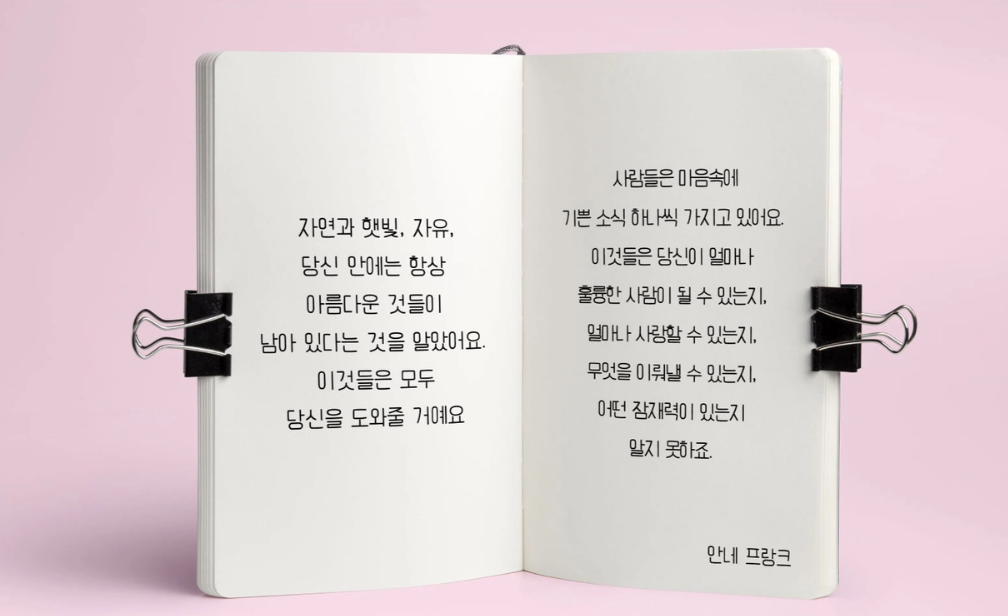
다이어리체 — 얼리폰트에서 배포하는 무료 폰트입니다. 또박또박한 필기감에 자연스러운 글자 변화를 더한 아담하고 정감 있는 손글씨체
얼리폰트가 배포하는 손글씨 서체입니다. 얼리폰트는 기업 전용서체 제작을 본업으로 하는 회사인데, 이 서체를 무료로 풀어 이름을 알린 것으로 알려져 있습니다.
제작사가 쓴 소개가 성격과 쓰임을 한꺼번에 말해 줍니다. 한 글자 한 글자 반듯하게 다이어리에 쓴 글씨처럼 손글씨지만 반듯한 매력의 서체이고, 유튜브 자막이나 귀여운 폰트가 필요한 곳에 추천한다는 것입니다. 파일에서 재어 보면 받침 유무에 따른 높이 차가 거의 없는 네모틀이라, 손글씨인데도 글줄이 흐트러지지 않습니다.